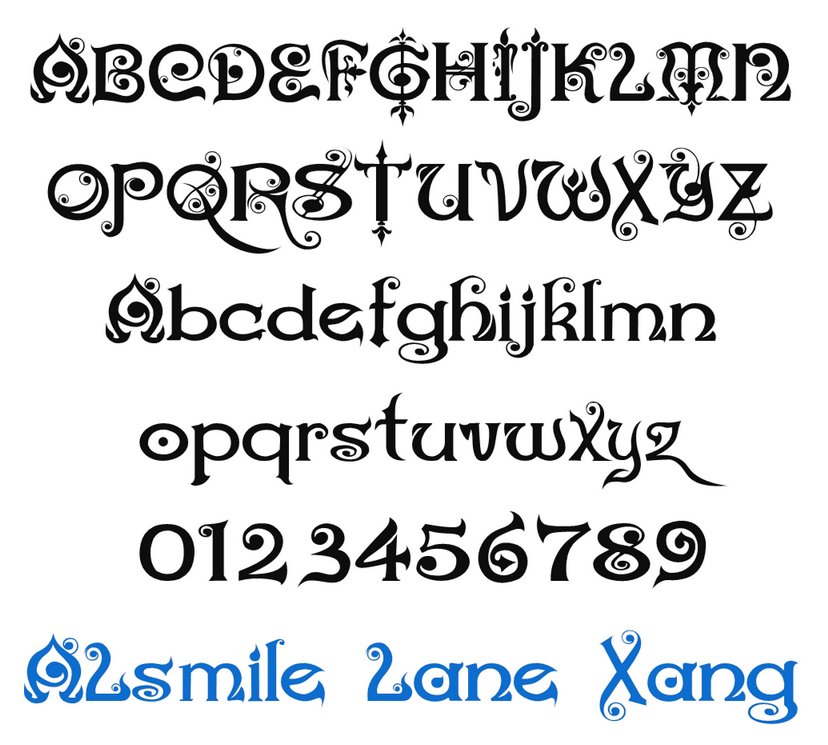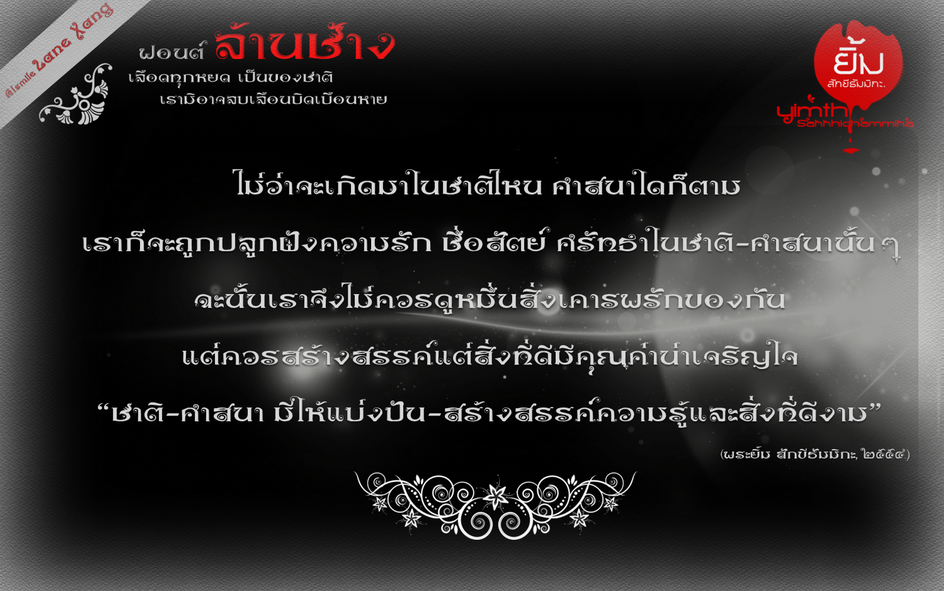
Alsmile Lane Xang (ฟรีวิว)
พอดีเมื่อคืนลองปรับแก้ ลบล้างตัว Eng. แล้วทำใหม่ให้หมด (เอาแบบสุดฝีมือ :43:)
โดยส่วนตัวแล้วยังไม่เคยพบคนอื่นทำฟอนต์สไตล์นี้ ถึงมีก็คิดว่าน้อยมาก
ส่วนมากก็จะทำแบบดัดแปลงจากฟอนต์ต่างชาติมา อย่างเช่น แฮร์รี่ ฯลฯ
ลองพิมพ์เนื้อความดู
ตัวนี้เป็นตัวที่พัฒนาจากตัวแรก แต่เน้นที่ตัว ช. ครับ
อีกภาพ
ตัวนี้ต้องการให้คำนิยามของคำว่า "ล้านช้าง" หมายถึงประเทศลาวผ่านตัวอักขระในทัศนคติและการรับรู้ส่วนตัวครับ
ปิดท้าย
แต่ตัวนี้ออกแบบใหม่ให้หมด สังเกตตัว Eng น๊ะ
ไม่แน่ในว่าจะต้องปรับอะไรอีกไหม คิดว่าจะไม่ปรับแก้อีกแล้ว..คิดว่าเพียงพอแล้ว เหนื่อยครับ
รอให้โยมร่มไทรมา comment อยู่เหมือนกัน จะได้ปรับปรุงแก้ไขตัวเอง
ไม่ยอมผิดพลาดอยู่กับที่หรอกครับ ต้องเปลี่ยนให้มันดี ดีขึ้นเรื่อย ๆ
โห ภาษาอังกฤษสุดยอดครับ :07:
ขอดูเพียวๆ แบบไม่มีกราฟิกปะปนได้ไหมครับ
ตั้งใจทำให้อักขระแต่ละตัวแตกต่างกัน
ให้มีเอกลักษณ์ที่โดดเด่นต่างกัน แต่เมื่อรวมกันแล้วเข้ากันได้
ตัว Eng. ทุ่มเทมาก เจ็บใจที่เคยให้ความสำคัญกับมันน้อย กะจะทำให้ฝรั่ง Mund อาย(แต่ mund คงไม่รู้อะนะ  :43:)
ทุกตัวที่ทำ มันคือศิลปะครับ
ตัว Eng. ของ a ให้ดูในคำว่า Lane Xang นะครับไม่ได้แก้
งามจริง อย่างกับรูปวาดมากกว่าตัวอักษร  :25:
:05: โห อิจฉามากครับ ผมอยากดัดเส้นให้ได้ดังใจแบบนี้จัง แต่ดัดไม่เป็น
ตัวนี้หลวงพี่ได้พัฒนาไปเป็นอีกตัวหนึ่งแล้ว
เดี๋ยวทำเสร็จจะเอามาลงให้ชมกันครับ
ถ้าไม่มีใครมาเมนต์อะไรอีก แสดงว่าตัวนี้ผ่านได้แล้วใช่ม๊ะ
ฟอนต์แนวนี้ผมพูดตรงๆ ว่าคอมเม้นท์ไม่เป็นครับ ไม่ใช่แนวเลย :3005:
เพราะฟอนต์แบบนี้จะจัดเป็นอีกหมวดพิเศษคือ "ฟอนต์แฟนซี" ครับ
เอาความชอบของคนทำเป็นหลักดีกั่ว  :12: